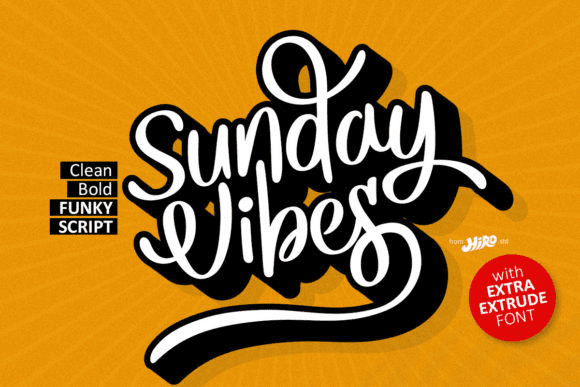
Название: Sunday Vibes Font
Sunday Vibes - это свежий, уникальный сценарий с беззаботным отношением и игривым краем.
Идеально подходит для причудливого, но непринужденного ощущения, он поставляется с большим выбором естественных лигатур.
Этот шрифт идеально подходит для логотипов, приглашений, свадебных конструкций, сообщений в социальных сетях и многое другое!